「神話」の雰囲気にぴったりな日本語フリーフォント
今回は、壮大で神秘的な世界観を演出できる 「神話」の雰囲気にぴったりな日本語フリーフォント をご紹介します。
神話といえば、遥か昔から語り継がれる神々の物語、英雄たちの伝説、神聖でどこか荘厳な空気感が大切です。そうした壮大な世界観を表現するには、フォントにも重厚感や神秘性、どこか古代を感じさせる存在感が求められます。力強い明朝体や装飾性のあるクラシカルな書体、石碑に刻まれたような威厳のある文字は、神話の雰囲気と抜群の相性を持っています。
今回は、ゲームタイトルやファンタジー作品、TRPG、物語系デザインなどにもぴったりな、“神々の時代”を感じさせる日本語フリーフォントをピックアップしました。壮大な世界観を作りたい方は、ぜひ参考にしてみてください。
神々の時代を感じる。神話の雰囲気にぴったりな日本語フリーフォント
以下のサンプルのように、“神話”の世界観にぴったりなフォントをご紹介します。神々しさや荘厳さを感じるクラシカルなフォントから、古代文字を思わせる装飾的な書体、ファンタジー作品に登場しそうな幻想的なフォントまで、文字だけでも壮大な物語を感じさせる魅力があります。
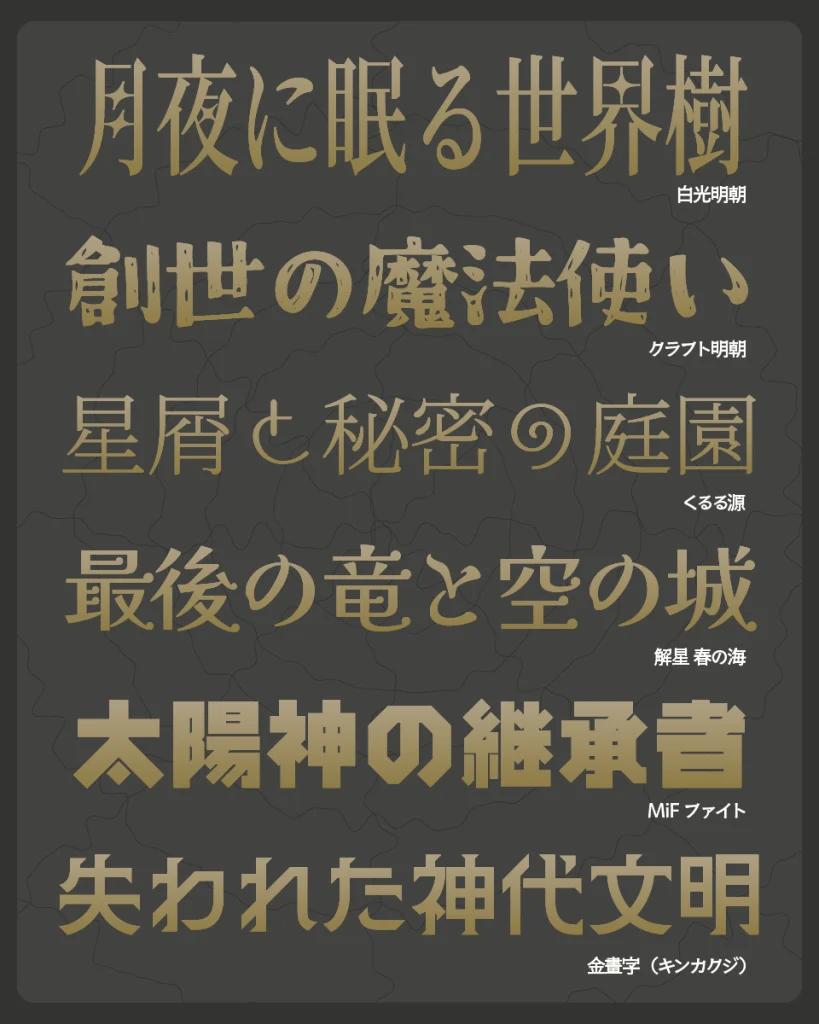
白光明朝
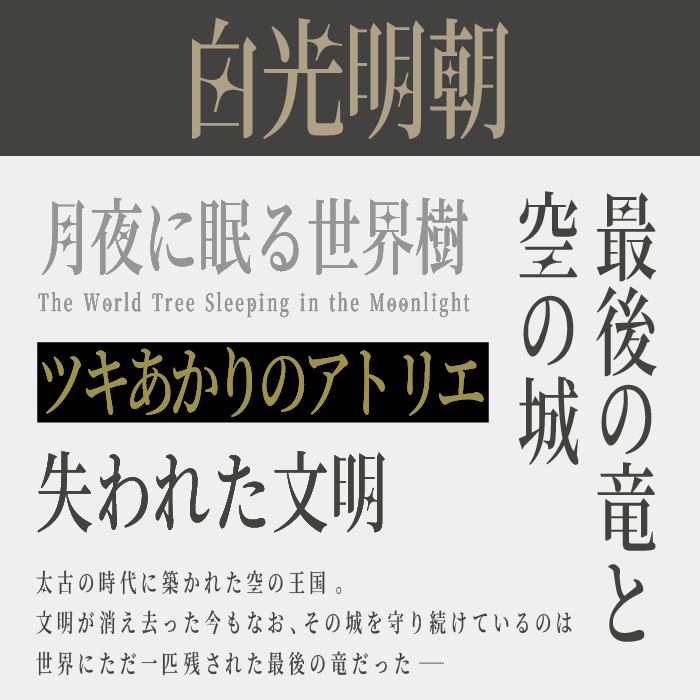
| 活用シーン例 | 精霊モチーフ、自然神話、幻想小説、優しいファンタジー作品 |
白光明朝は、明朝体の持つ伝統的な美しさを残しながら、柔らかな丸みを加えた独特な日本語フリーフォントです。神話作品の中でも、精霊や自然神、優しく幻想的な物語と相性が良く、どこか温かみのある神秘的な雰囲気を演出できます。硬すぎない柔らかな神話世界を表現したい場面におすすめのフォントです。
京華老宋体
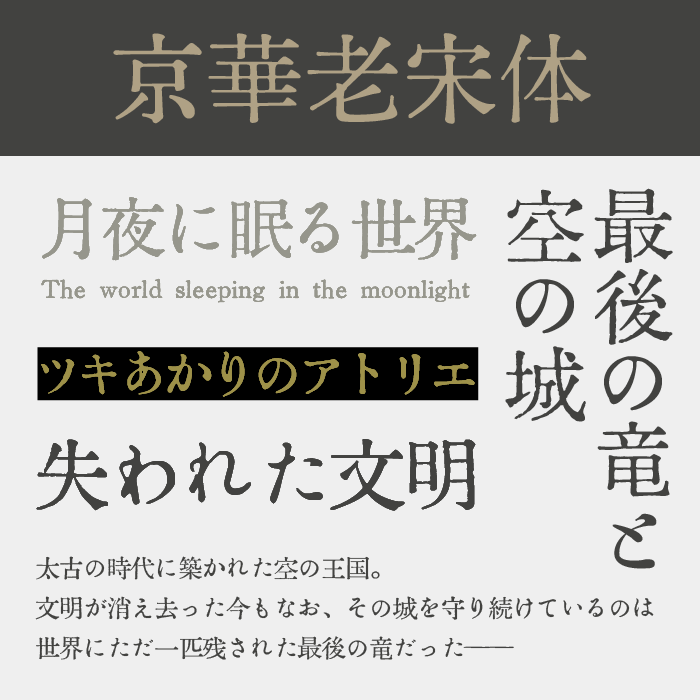
| 活用シーン例 | 古代王国モチーフ、神話タイトル、神殿デザイン、歴史ファンタジー |
京華老宋体は、古典的な宋朝体の雰囲気を色濃く残した、格式高い印象の日本語フリーフォントです。歴史の重みを感じさせる端正な造形が特徴で、まるで神殿に刻まれた古代文字のような荘厳さがあります。神話や伝承の世界観に自然と溶け込み、壮大で気品あるビジュアル表現にぴったりなフォントです。
MiFファイト
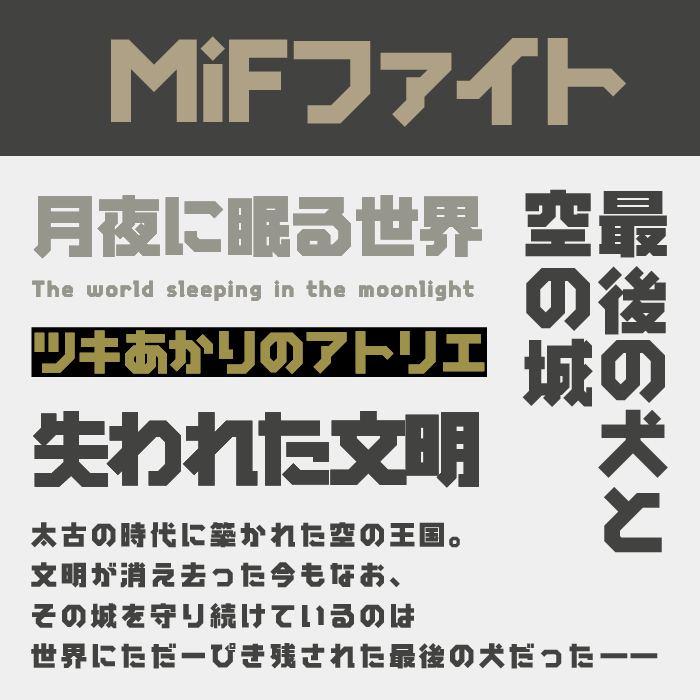
| 活用シーン例 | 古代文明デザイン、SF神話、遺跡モチーフ、ゲームUI、異世界ビジュアル |
MiFファイトは、直線的で幾何学的なデザインが特徴的な日本語フリーフォントです。古代文明や失われたテクノロジーを感じさせる独特な雰囲気があり、神話の中でも未来神話や遺跡をテーマにしたビジュアルと相性の良いフォントです。神秘性と無機質さが共存した個性的なフォントです。
幻ノにじみ明朝
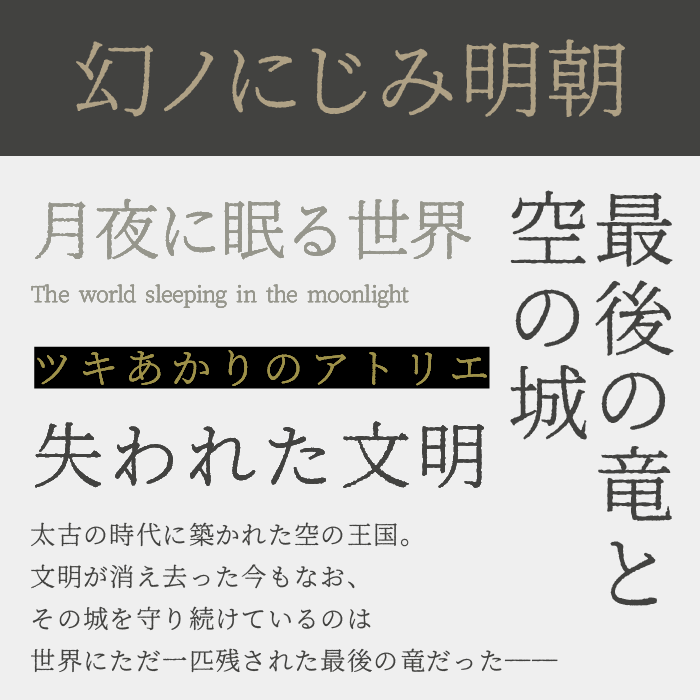
| 活用シーン例 | 広告デザイン/サムネイル/テロップ/バナー/パッケージ/ポスター/同人誌 |
幻ノにじみ明朝は、にじんだような独特の輪郭が幻想的な空気を生み出す日本語フリーフォントです。まるで古い書物や忘れられた記録に記された文字のような質感があり、神秘的で少し不安定な世界観を演出できます。神話や伝説を感じさせる演出に非常に相性の良いフォントです。
うつくし明朝体
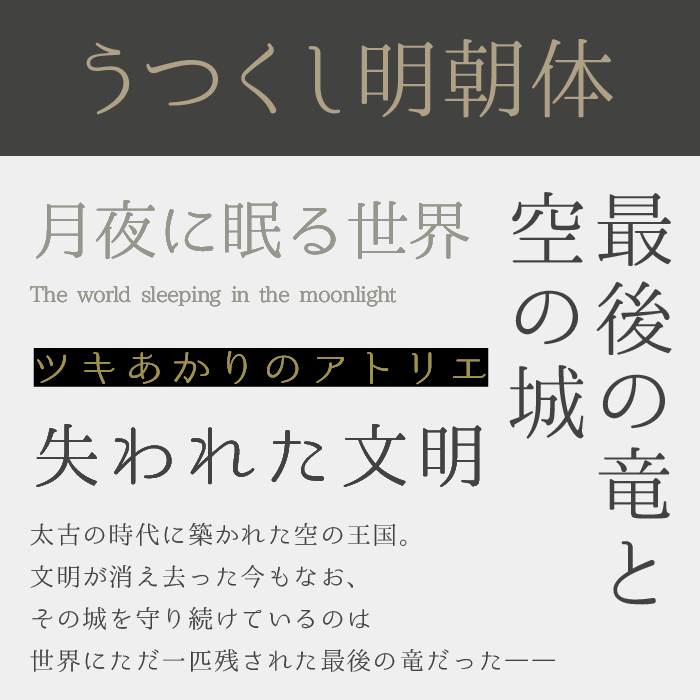
| 活用シーン例 | 神話系タイトル、幻想小説、ファンタジー作品、世界観重視のビジュアル、静かな物語演出 |
うつくし明朝体は、繊細で流れるような線の美しさが印象的な日本語フリーフォントです。上品で静かな空気感があり、神話や伝承に登場する幻想的な世界観を自然に演出できます。どこか儚さも感じられ、壮大で美しい物語のタイトル表現にぴったりなフォントです。
あおさぎ
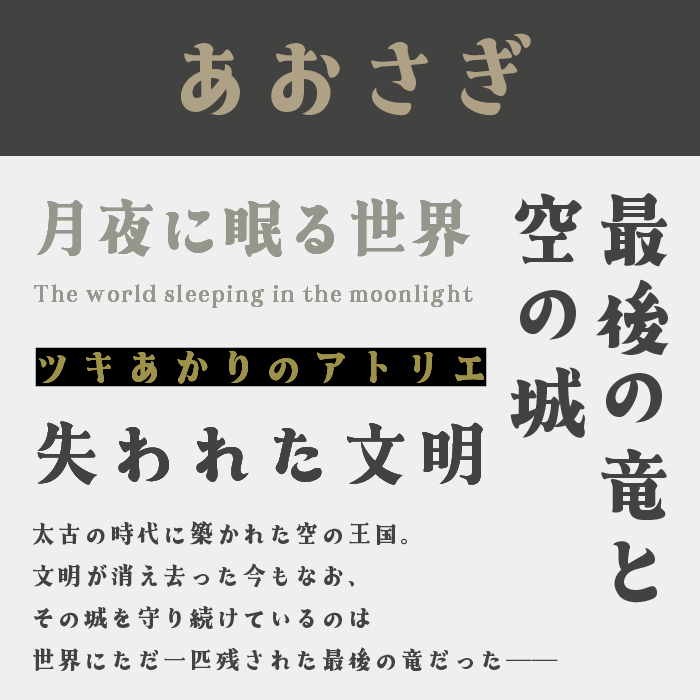
| 活用シーン例 | 冒険ファンタジー、英雄伝説、RPGタイトル、重厚感のあるロゴ、壮大な世界観演出 |
あおさぎは、どっしりとした重厚感を持ちながらも、どこか古風で品のある雰囲気を感じる日本語フリーフォントです。力強い文字の存在感があり、英雄譚や壮大な冒険物語のタイトルにもよく映えます。王道ファンタジーや神話作品らしいスケール感を表現しやすいフォントです。
花園明朝
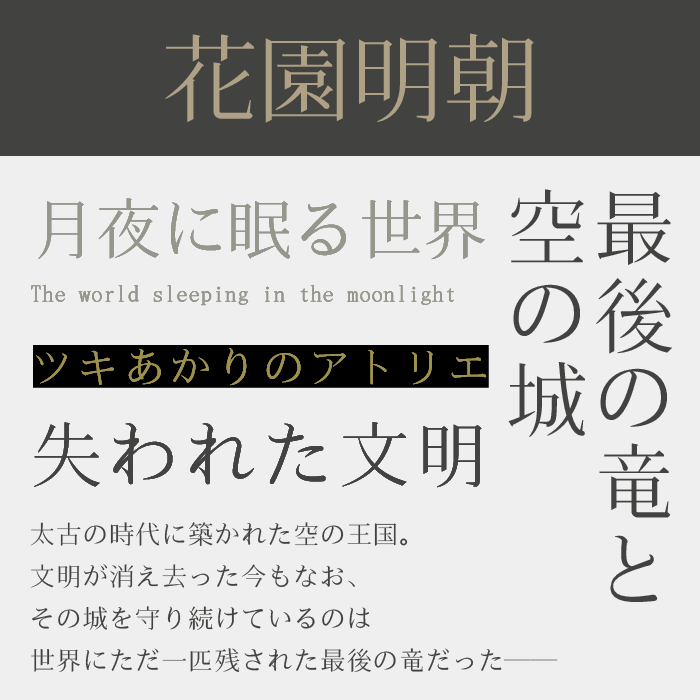
| 活用シーン例 | 和風神話、日本神話コンテンツ、歴史系デザイン、伝承モチーフ |
花園明朝は、王道の美しい明朝体をベースにしながら、柔らかく優雅な印象を持つ日本語フリーフォントです。神々しさや荘厳さを感じさせる雰囲気があり、日本神話や古代伝承のような静かで格式高い世界観にぴったりなフォントです。
スミカク
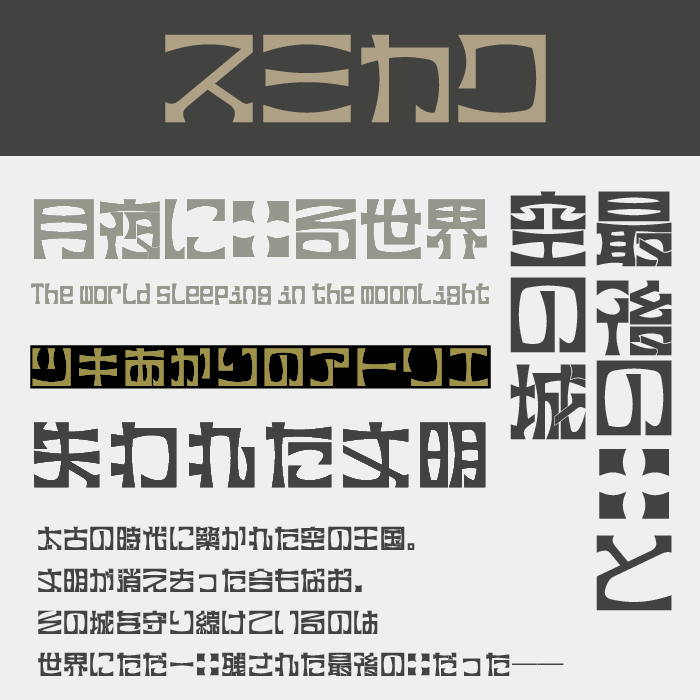
| 活用シーン例 | 異世界作品、古代文明演出、ゲームロゴ、架空文字風デザイン、SFファンタジー |
スミカクは、独特にデフォルメされた字形が特徴的な個性派日本語フリーフォントです。古代文字のような不思議さや未知の文明を感じさせる独特なデザインが魅力で、普通の明朝体では表現できない異世界感を演出できます。神話の中でも特殊な文明表現にぴったりなフォントです。
金畫字
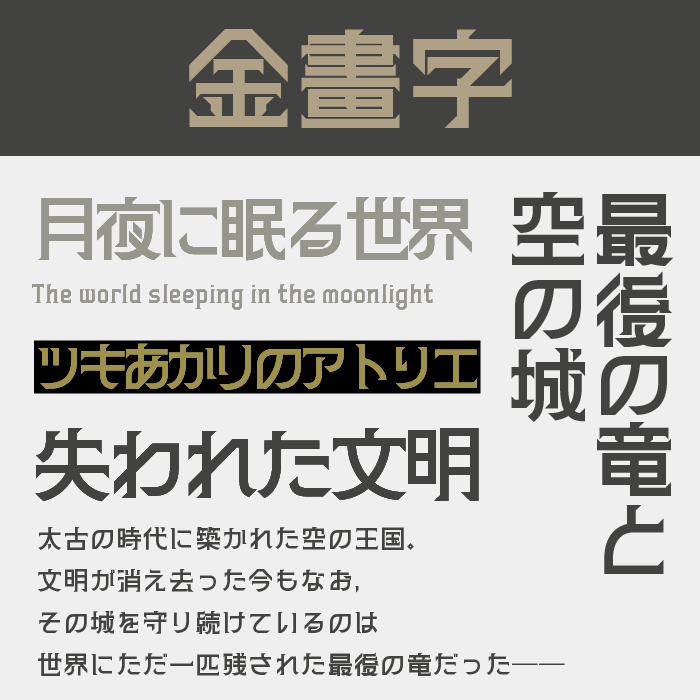
| 活用シーン例 | 神殿モチーフ、古代遺跡デザイン、壮大なタイトル、ゲームロゴ |
金畫字は、非常に力強く硬質なシルエットを持った日本語フリーフォントです。石碑や神殿に刻まれた文字のような重厚感があり、神話に登場する古代王国や神々の力を感じさせる独特な迫力があります。存在感の強いタイトル制作に向いているフォントです。
解星 春の海
| 活用シーン例 | 精霊モチーフ、月や海をテーマにした作品、幻想小説、神秘的ビジュアル |
解星 春の海は、流れるような筆致と繊細なバランスが魅力の日本語フリーフォントです。幻想的で美しい雰囲気が非常に強く、静かな神話や月、海、精霊といった自然をテーマにした神秘的な表現にぴったりです。儚く美しい物語演出におすすめのフォントです。
くるる源
| 活用シーン例 | 魔法演出、異世界デザイン、神秘的タイトル、呪文風ビジュアル、幻想作品制作 |
くるる源は、柔らかな曲線と装飾的なデザインが特徴的な日本語フリーフォントです。文字そのものに独特な神秘性があり、古代文明や魔法、呪文のような不思議な空気感を演出できます。ファンタジー作品に独自性を加えたい場面で活躍するフォントです。
クラフト明朝
| 活用シーン例 | 古代遺跡演出、神話タイトル、ダークファンタジー、石碑風デザイン、冒険ゲームロゴ |
クラフト明朝は、クラフト感のある独特な質感と、削り出したような荒さが魅力の日本語フリーフォントです。古い石板や遺跡に刻まれた文字を思わせる独特な表情があり、神話や伝承の中でも古代文明寄りの世界観と非常に相性の良いフォントです。